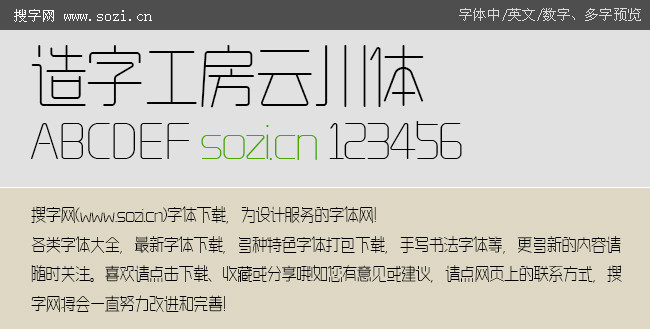
造字工房云川體
搜字網(wǎng)給大家提供一款造字工房云川體中文字體下載,造字工房云川體是一款橫平豎直的細(xì)體字體,筆畫(huà)纖細(xì)舒潤(rùn),簡(jiǎn)約洗練,起承轉(zhuǎn)合圓勁均勻,疏密有致。其字形古樸清俊,處處平衡對(duì)稱、方圓中寓,古風(fēng)雄健。適合應(yīng)用于書(shū)籍裝幀設(shè)計(jì)、包裝設(shè)計(jì)、海報(bào)設(shè)計(jì)、網(wǎng)頁(yè)設(shè)計(jì)等應(yīng)用。(本字體為個(gè)人非商用版,如需要商用請(qǐng)聯(lián)系官方購(gòu)買版權(quán))